2020年11月22日,方正IT旗下方正电子主办的“方正2020字体设计大会”在北京模范书局·诗空间正式拉开帷幕。大会上,第十届『方正奖』字体设计大赛获奖名单一一揭晓,字体设计新生代崭露头角;方正2020字体设计实践系列成果精彩纷呈。400多万国内外设计师及爱好字体的观众,通过线上直播的方式,共同见证了此次活动的召开。
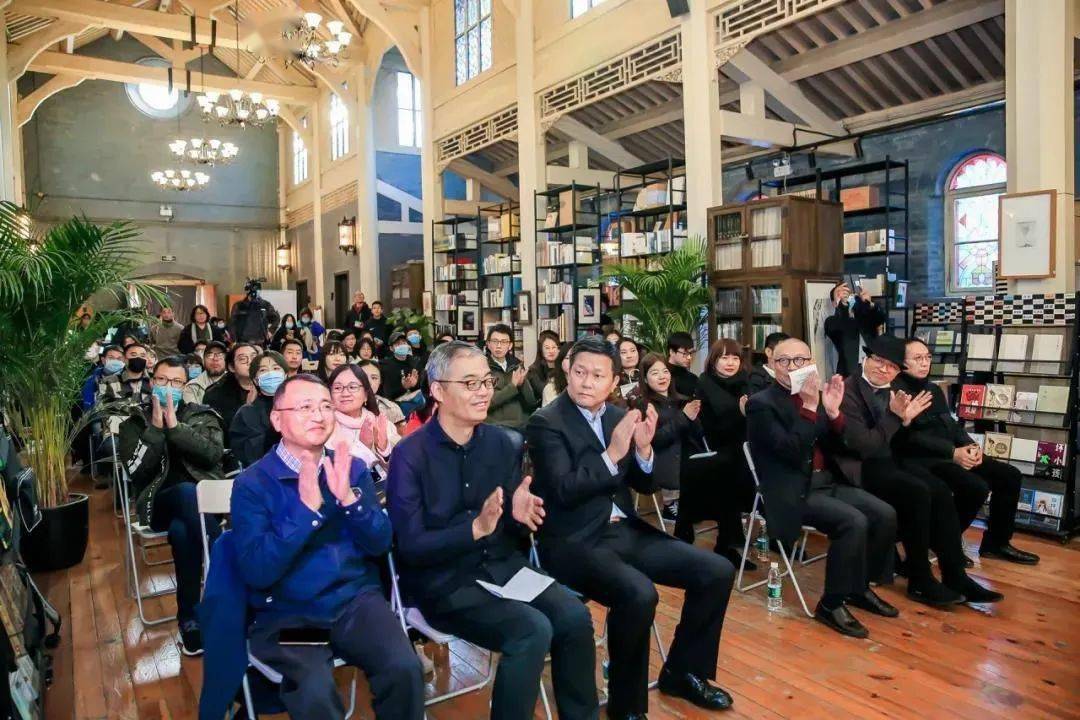
▲活动现场
大赛自2019年6月18日正式启动以来,收到参赛作品共计3922件,组织学生参赛的院校有300多所,指导老师共400多名。受新冠疫情影响,十二位专家评委首次采用线上方式,经过多轮专业、细致、严谨的评审,共有52件参赛作品、23位指导老师、22家高校,获得本届大赛设置的字体类别奖、评审委员奖、优秀指导老师奖及优秀合作院校奖。
本届大赛注重字体设计实用性、规范性与艺术性的平衡,强调“字体为用而设计”。在竞赛类别上,延续了第九届大赛的设置规则,分中文专业组、中文学生组、拉丁文组三个竞赛单元,确保大赛在鼓励学生参赛的同时,能更好地引导字体设计的专业性。同时,大赛又以开放、包容的国际视野,充分挖掘优秀的西文字体设计创意。本次获奖作品中既有源于生活的有趣创意,也有对书法经典的汲取和提炼,选手们在创作的广度和深度方面,都很让人欣喜。
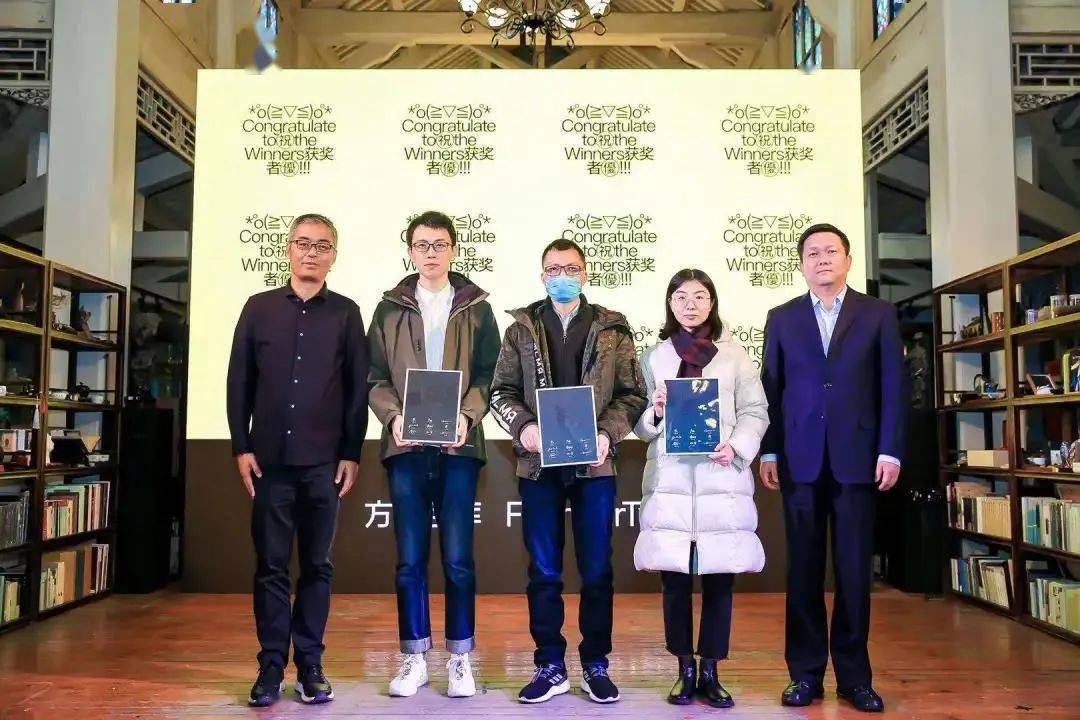
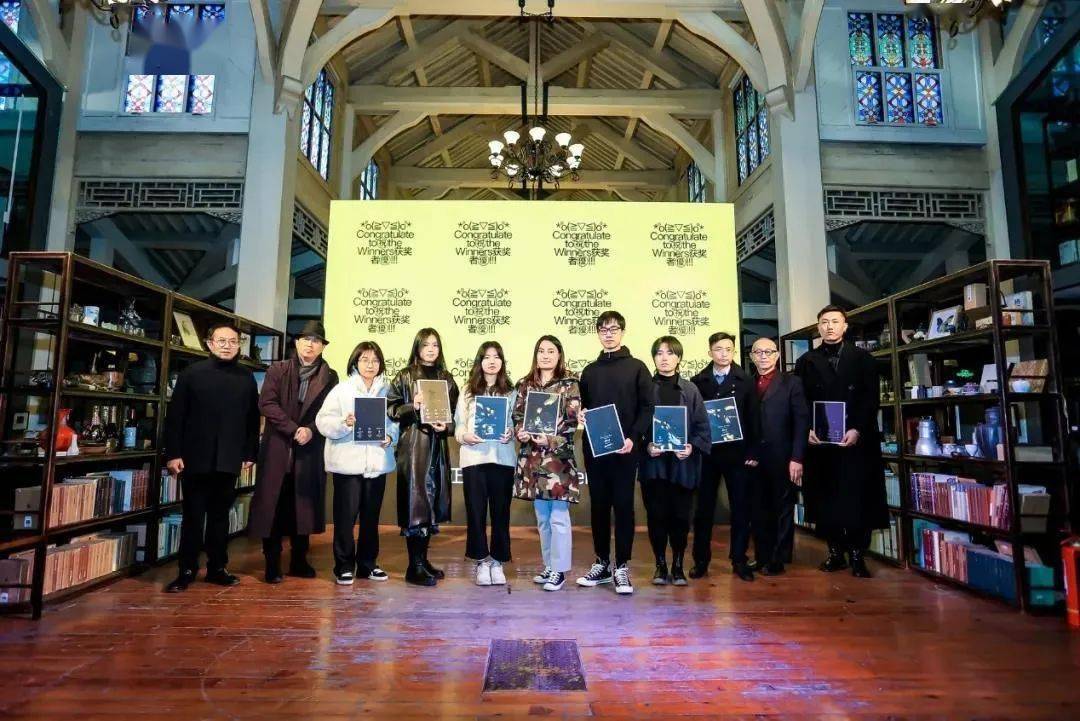
▲颁奖现场
『方正奖』字体设计大赛是中国第一个面向字体行业的设计类赛事,也是字体设计领域影响力最广、参与人数最多的专业赛事。2001年5月23日,在字库行业最艰难的时候,首届“北大方正奖”印刷字体设计大赛面向全社会征稿,此后大赛每两年一届,至今已成功举办十届赛事。
通过『方正奖』大赛,许多优秀的获奖作品被开发成为字库并服务于人们的生活,同时也为行业挖掘并输送了一大批出色的设计人才,有力推动中文字体设计的创新,加强中外文化交流,推动中国字体行业繁荣发展,弘扬中华民族古老的汉字文化。